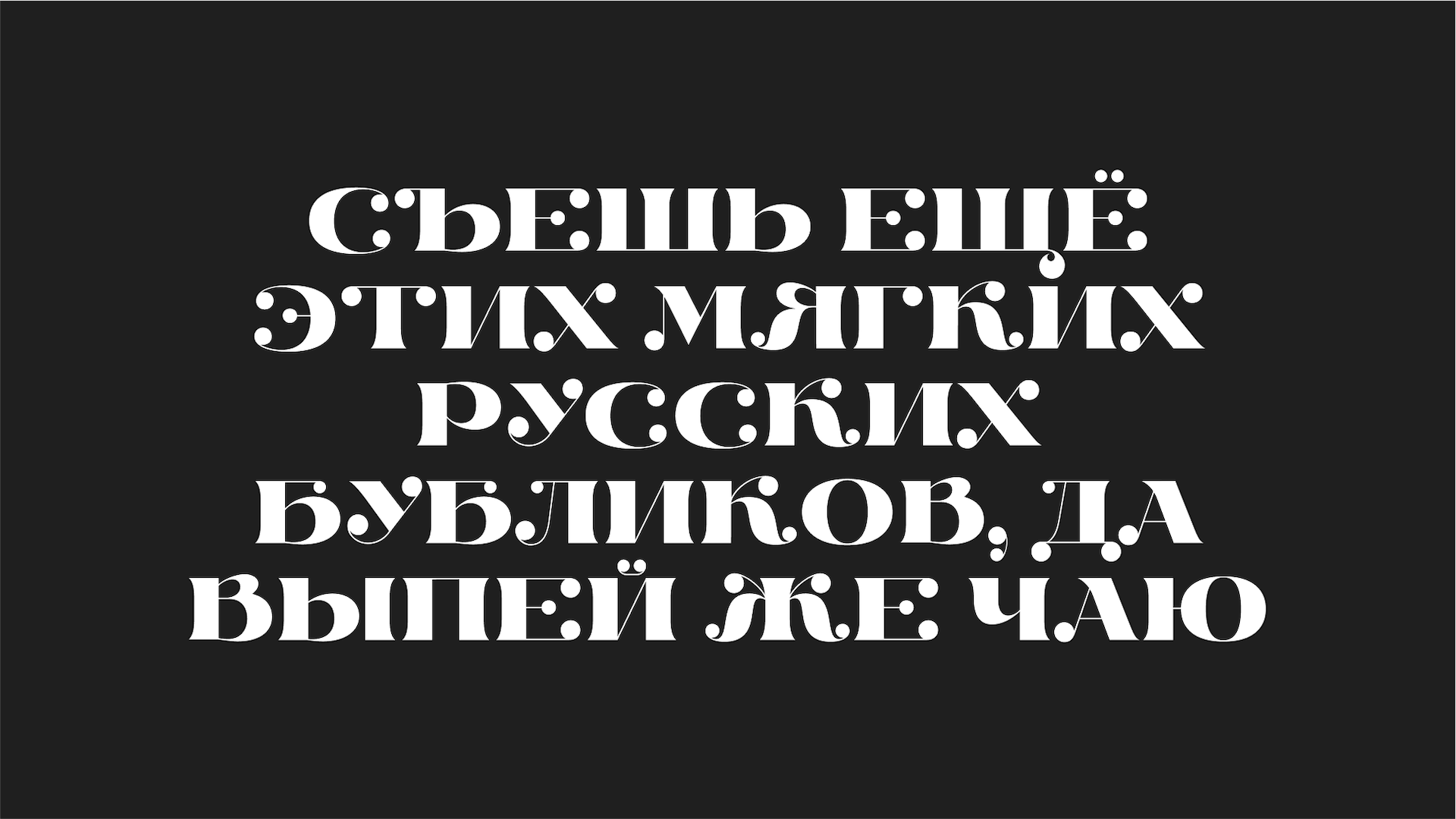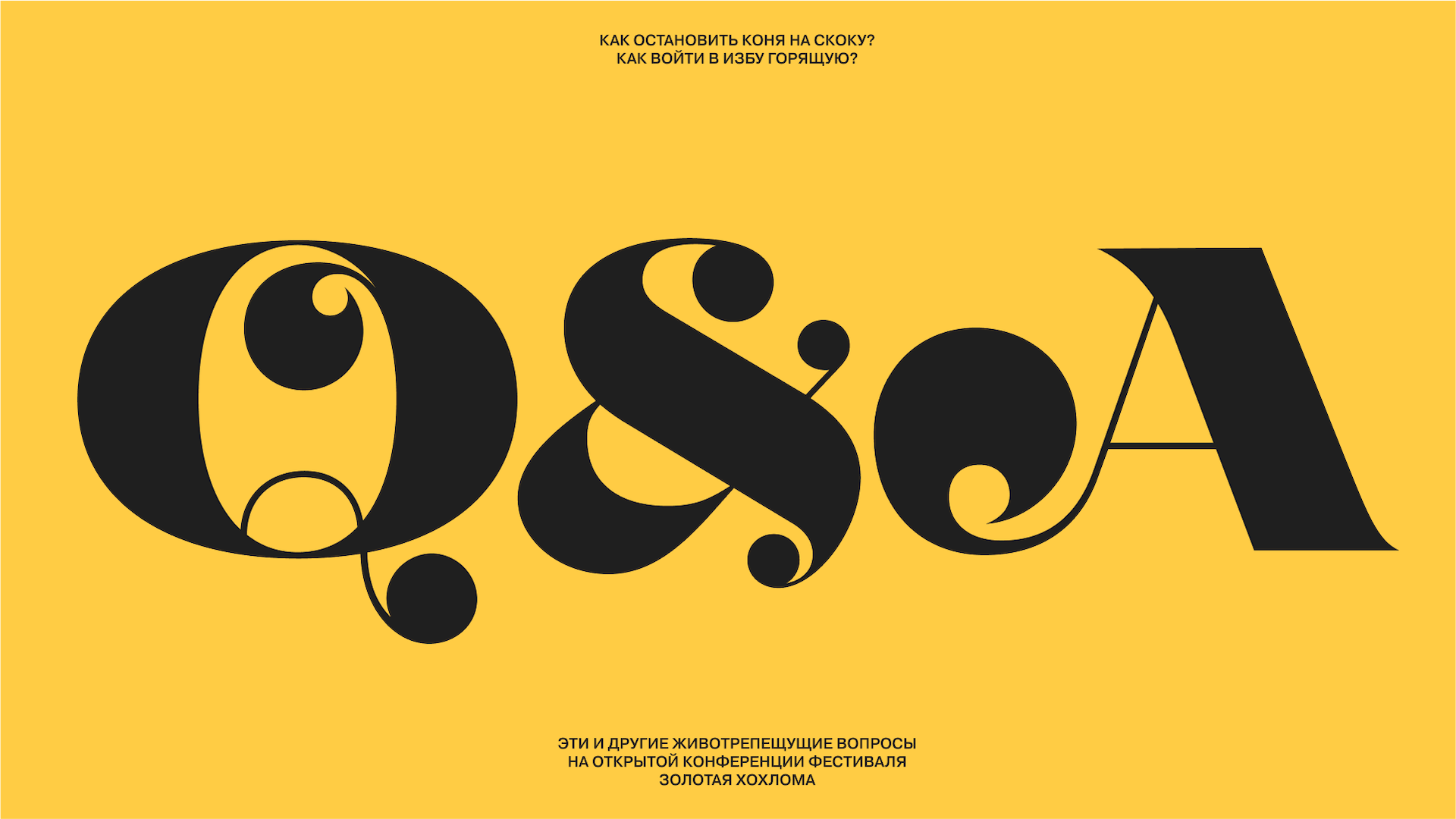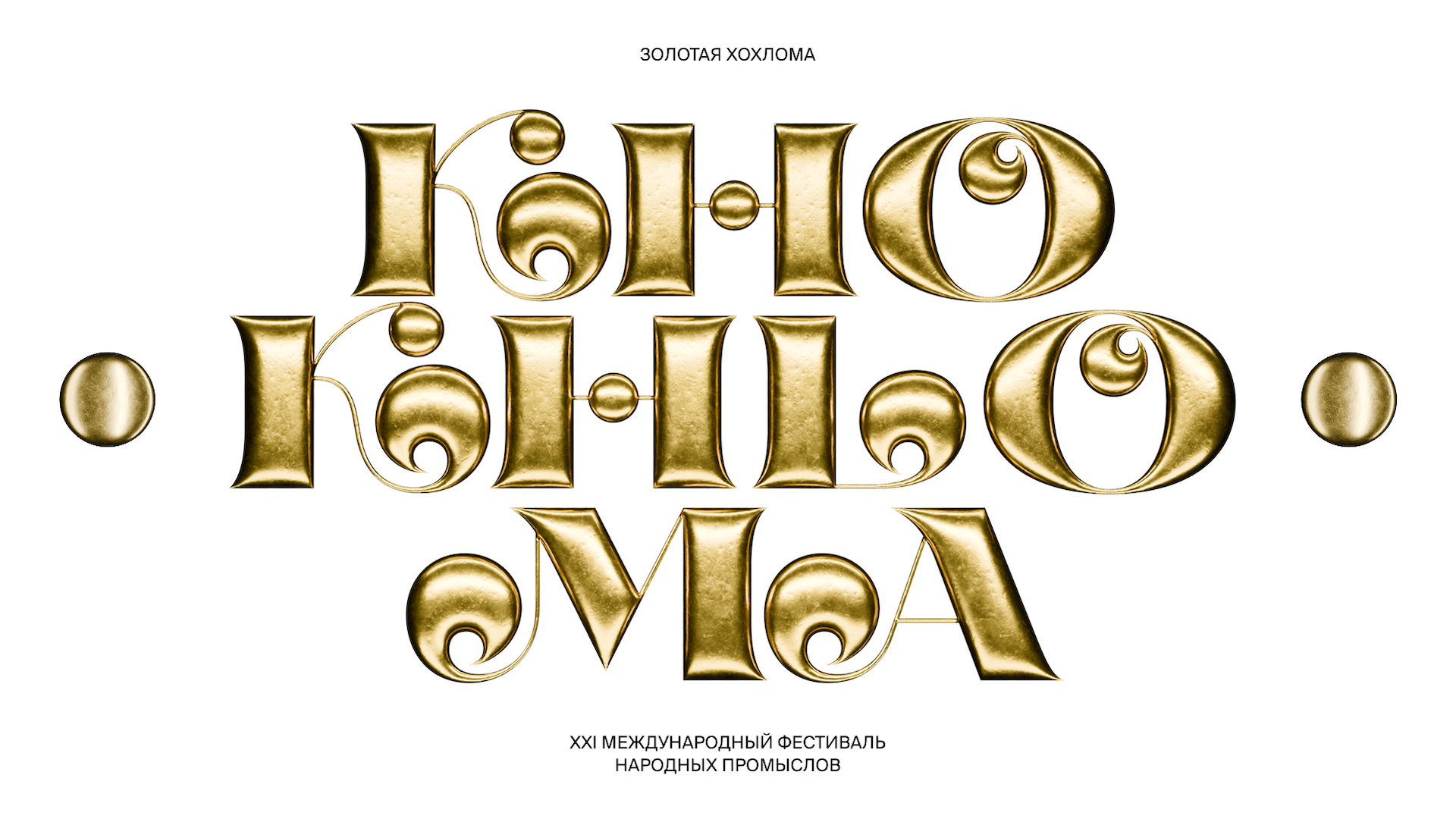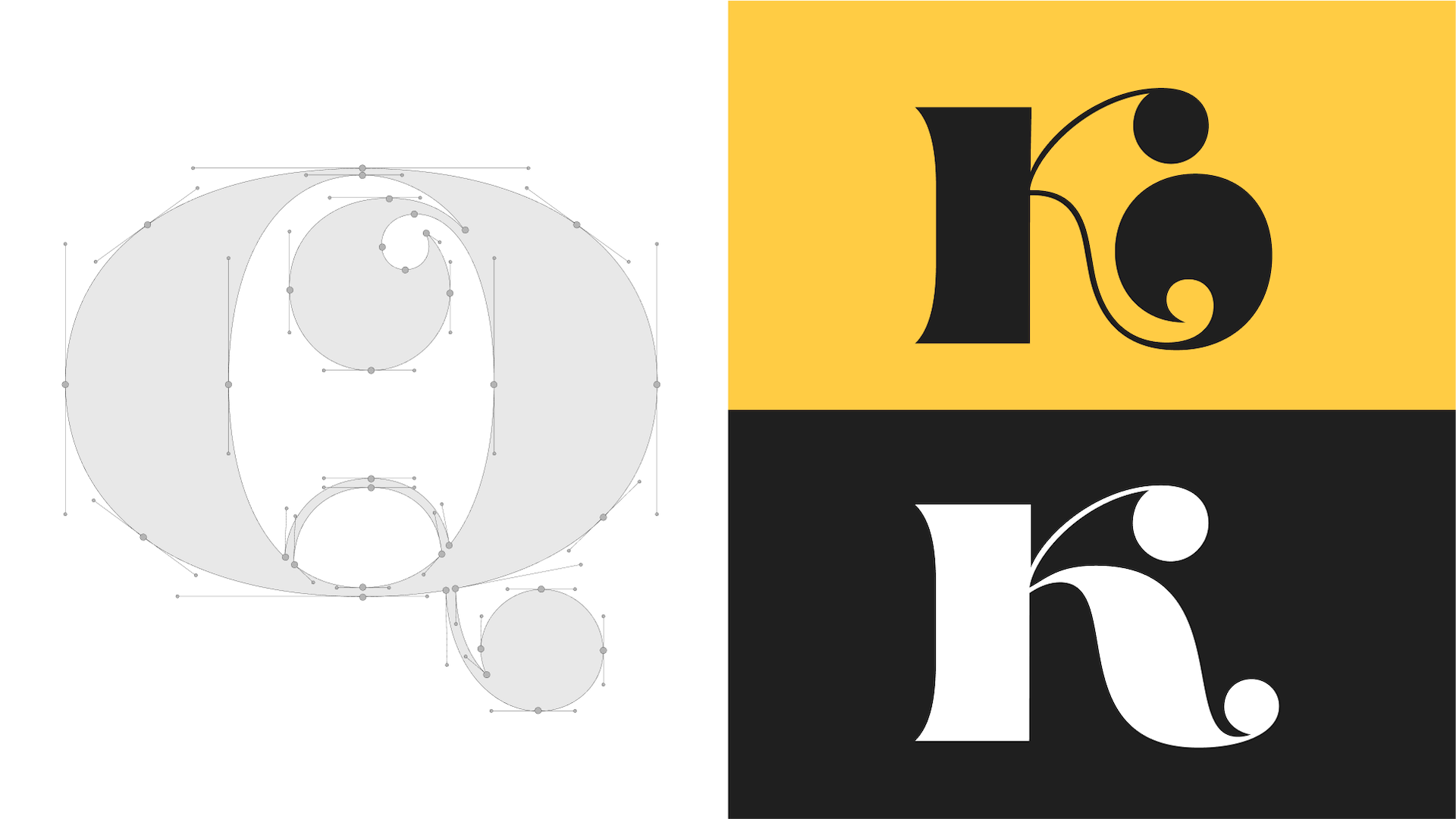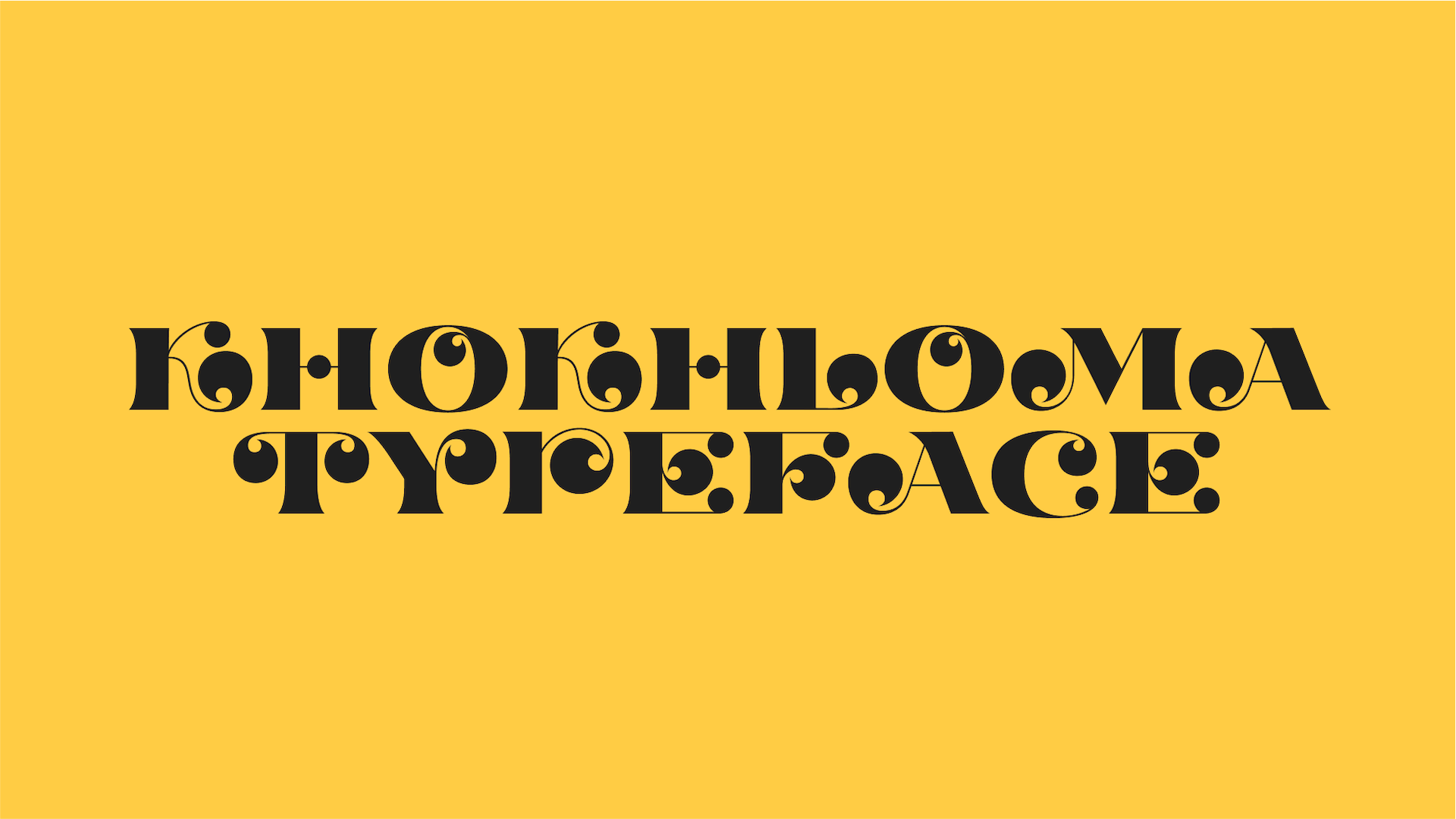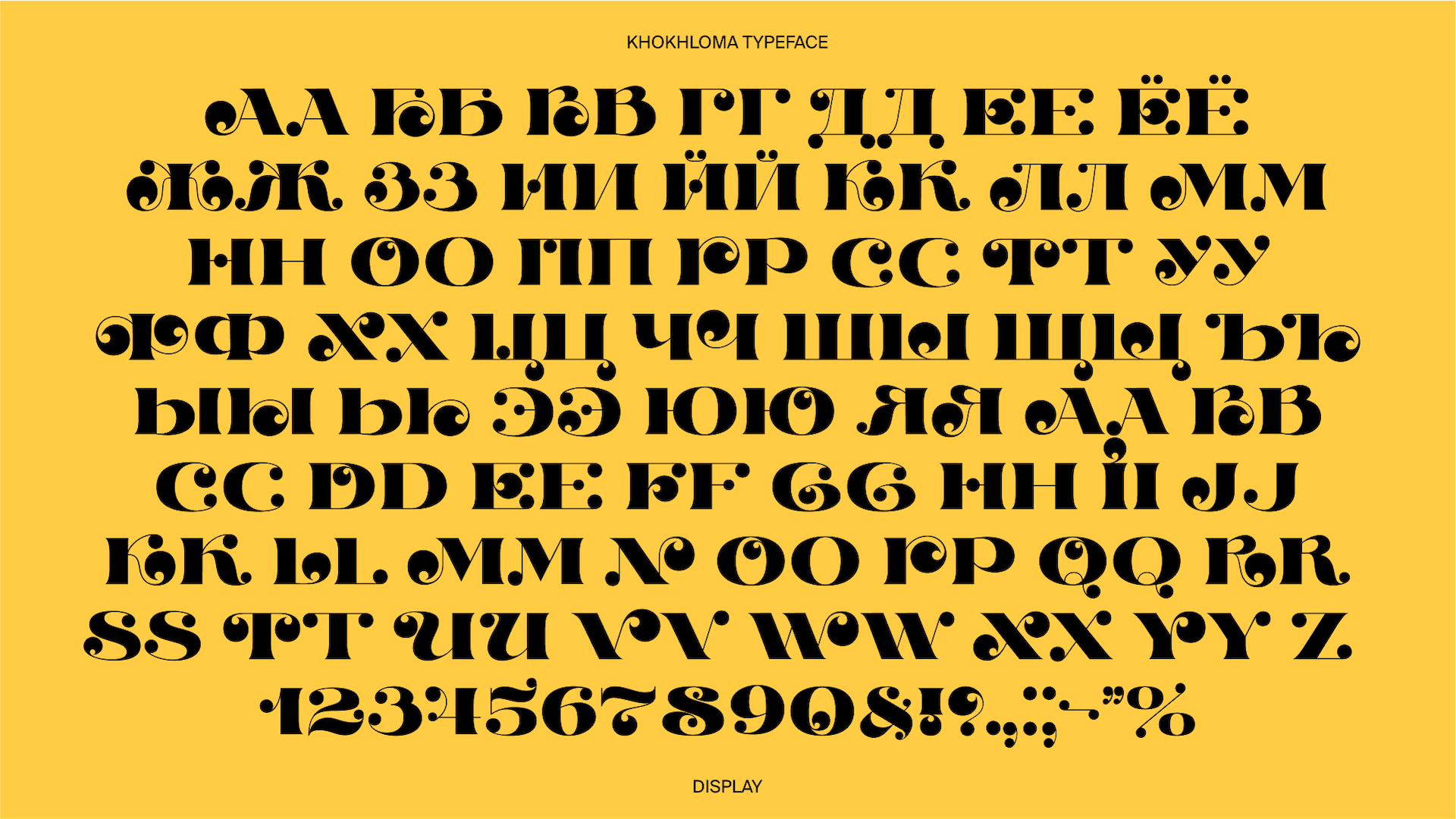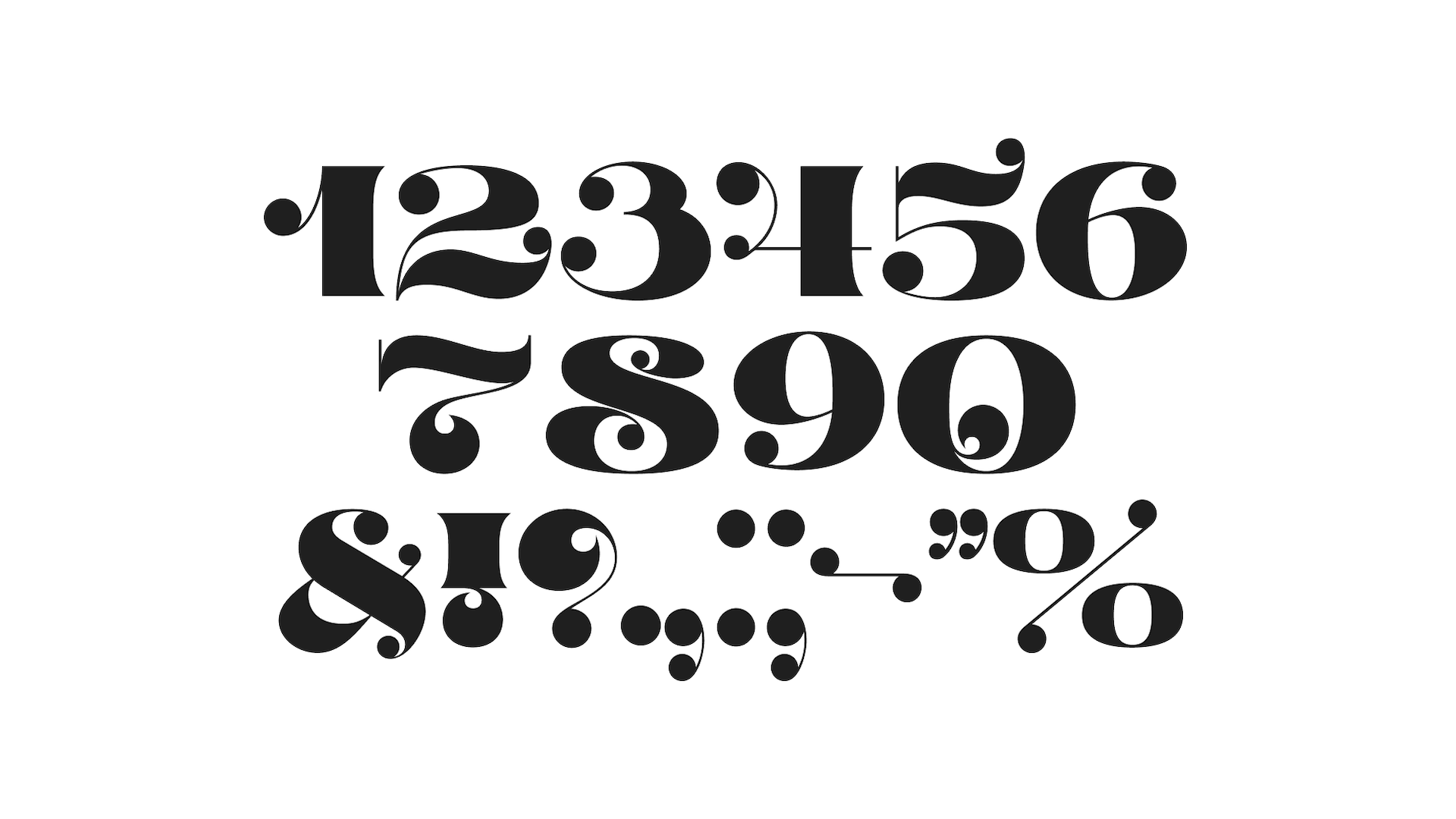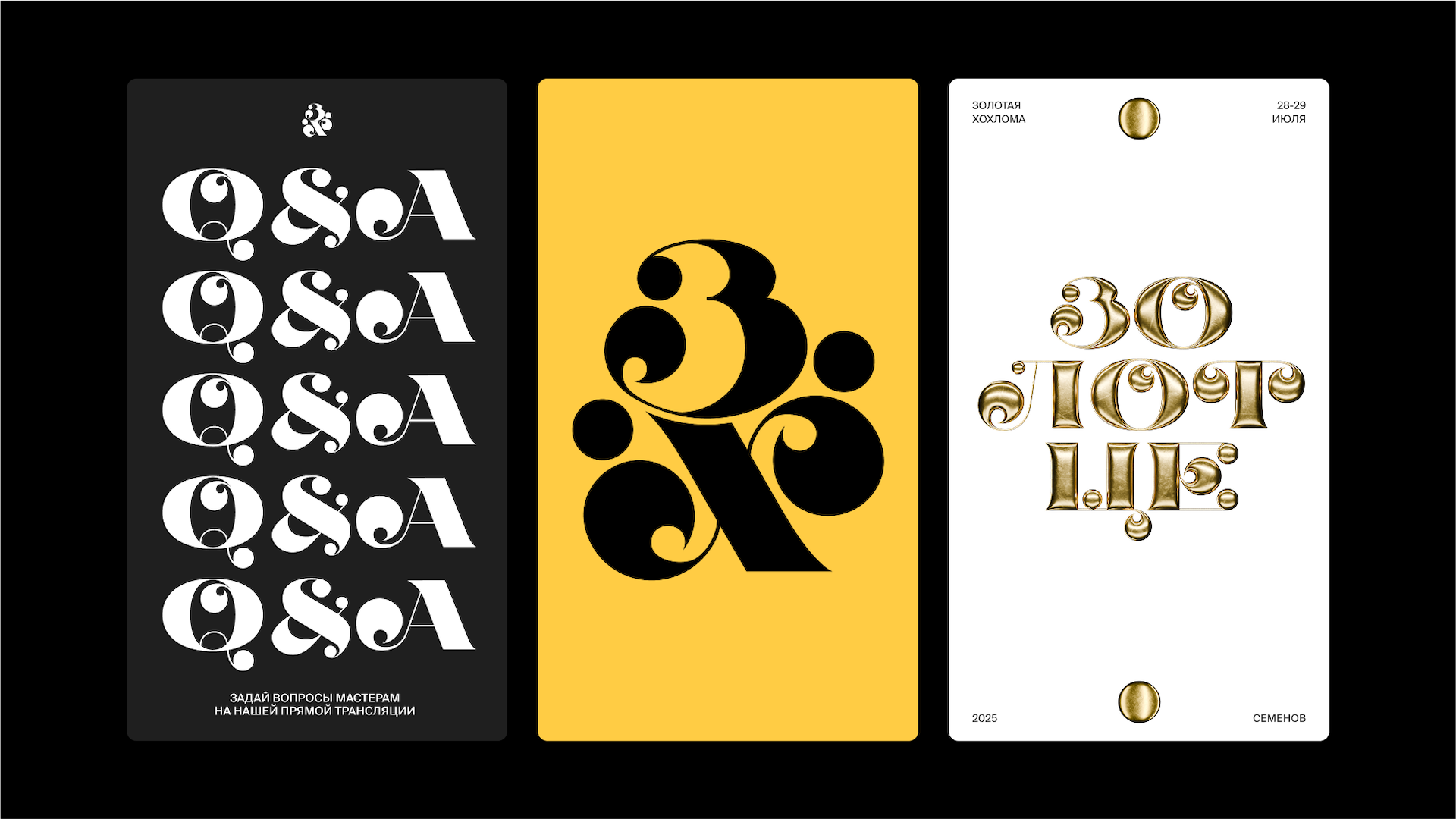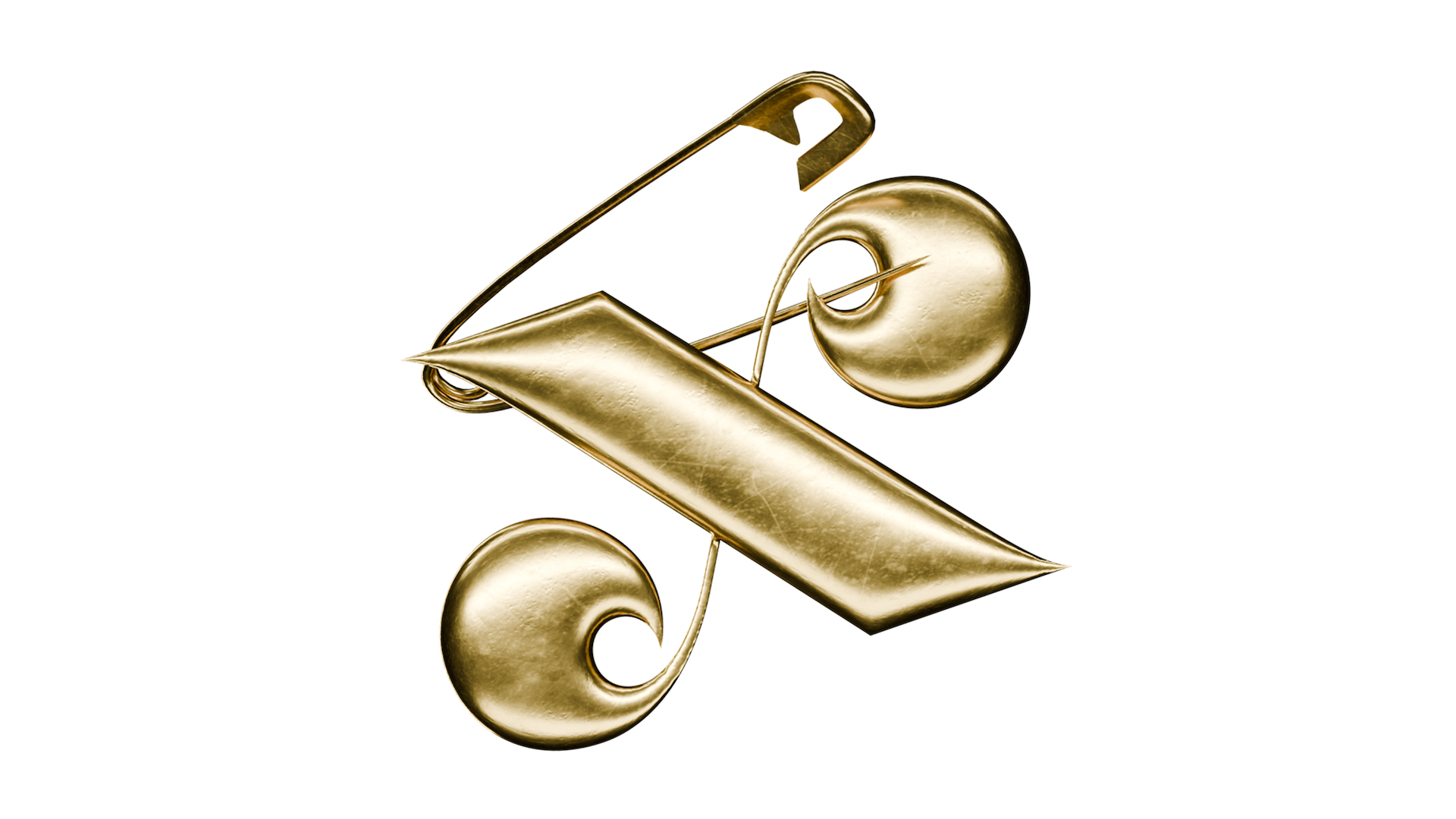
Khokhloma Typeface
Khokhloma Typeface был разработан в процессе создания айдентики для фестиваля «Золотая хохлома» в городе Семёнов.
Это мероприятие не только демонстрирует богатство самой росписи, но также способствует сохранению и развитию культурного наследия. Именно поэтому привычная нам хохломская пластика здесь становится основой для ультражирной ленточной антиквы.
Фестиваль Золотая Хохлома